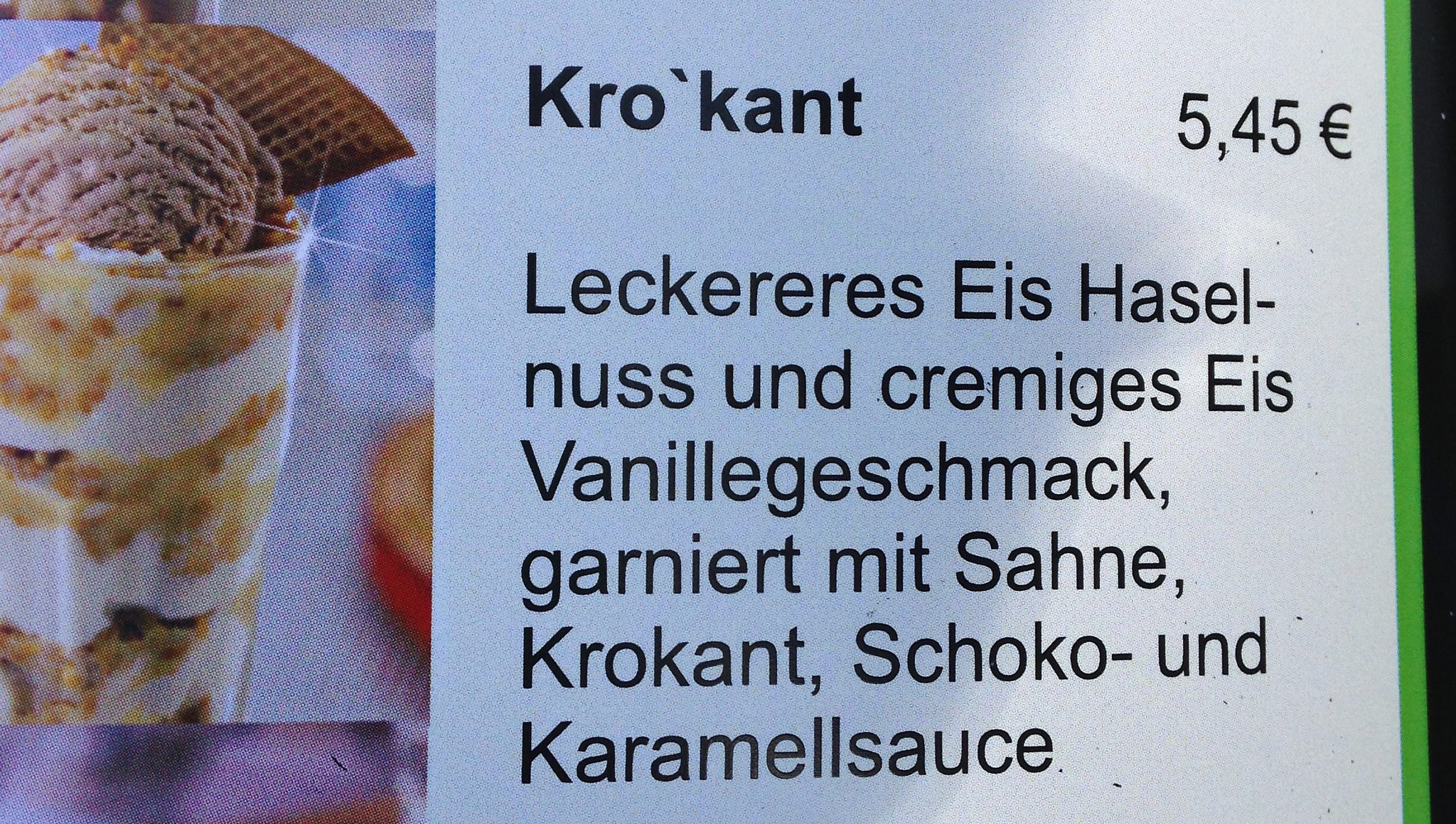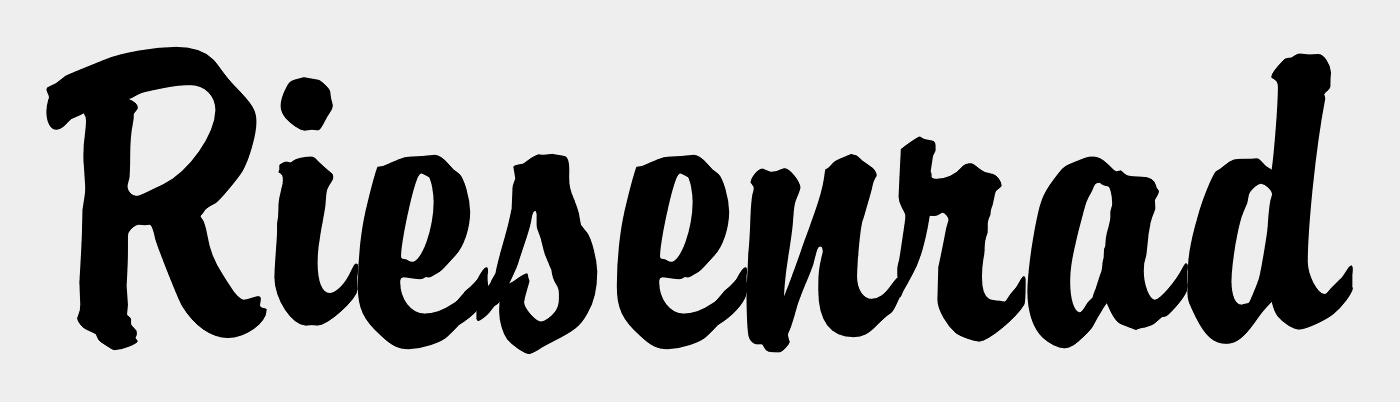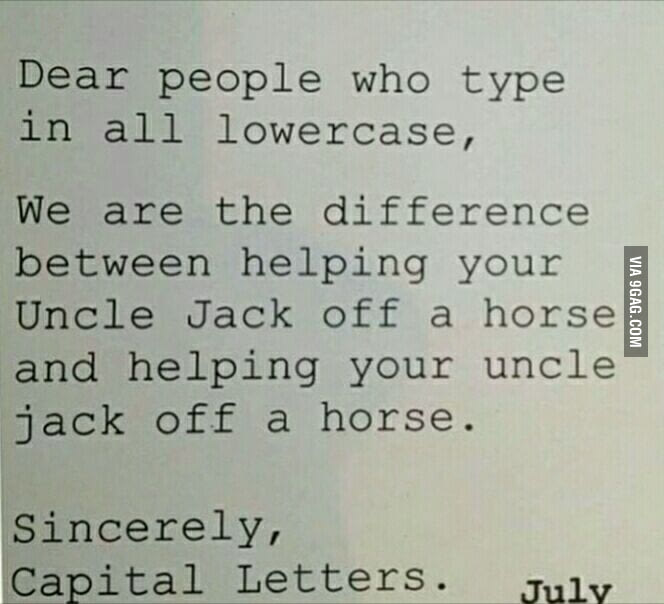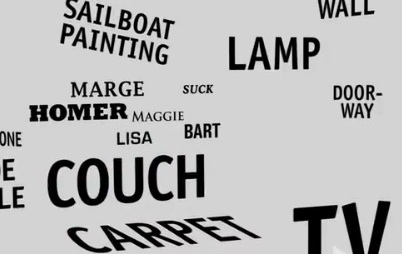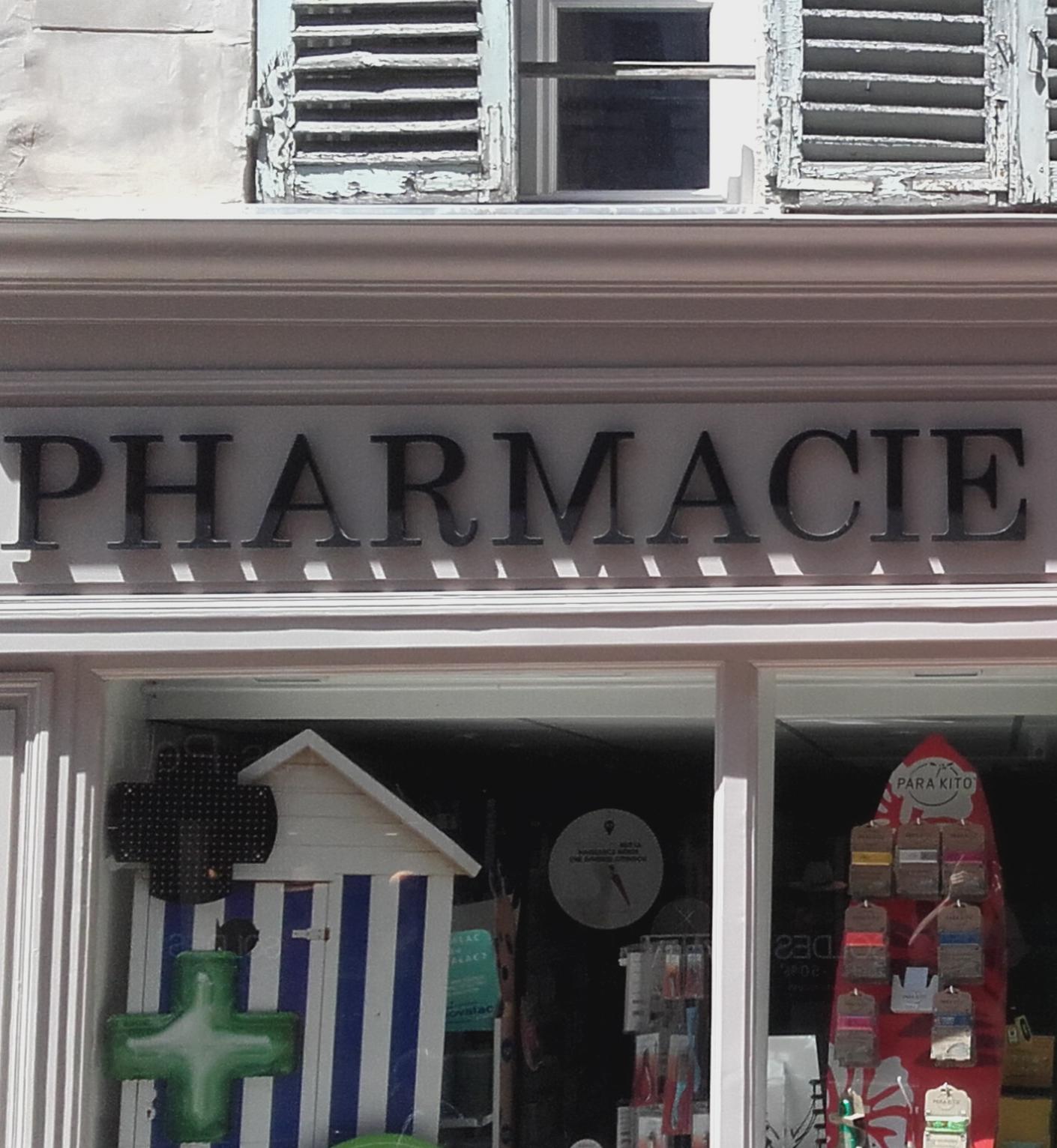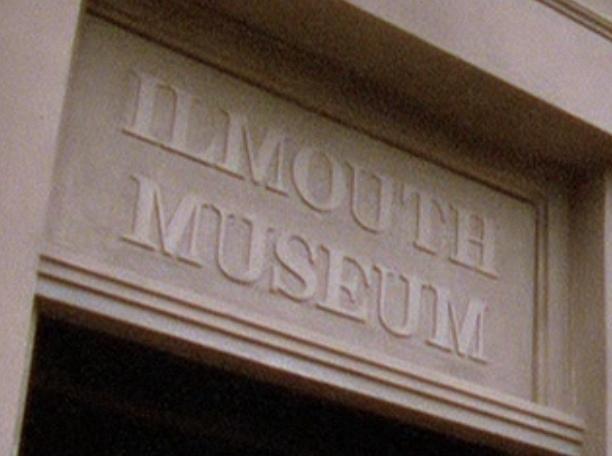
hatten wir das schon?
Yep, zuerst 2008 von Schwalbenkönig und – weil ich das auch nicht wusste – am 1. April von mir auch noch mal. Ist aber immer wieder großartig :cheer:
Neulich bei uns auf’m Altstadtfest:
Was ist denn da passiert?
Wenn das ursprüngliche s abgegangen ist und ersetzt worden wäre, wäre die Lücke ja kleiner :-?
War da fälschlicherweise ein ß?
Gesehen in Frankreich.
Und direkt noch einer von der Sorte:
Der Fairness halber muss gesagt werden, dass das Schild nur für ein paar Sekunden in einer Serie zu sehen war.
Apropos Serie:
Hatten wir das schon?
Es wird immer schlimmer … :cry:
Oder meinen die den mit der Panda-Maske? Dann aber bitte Cro’kant :-P